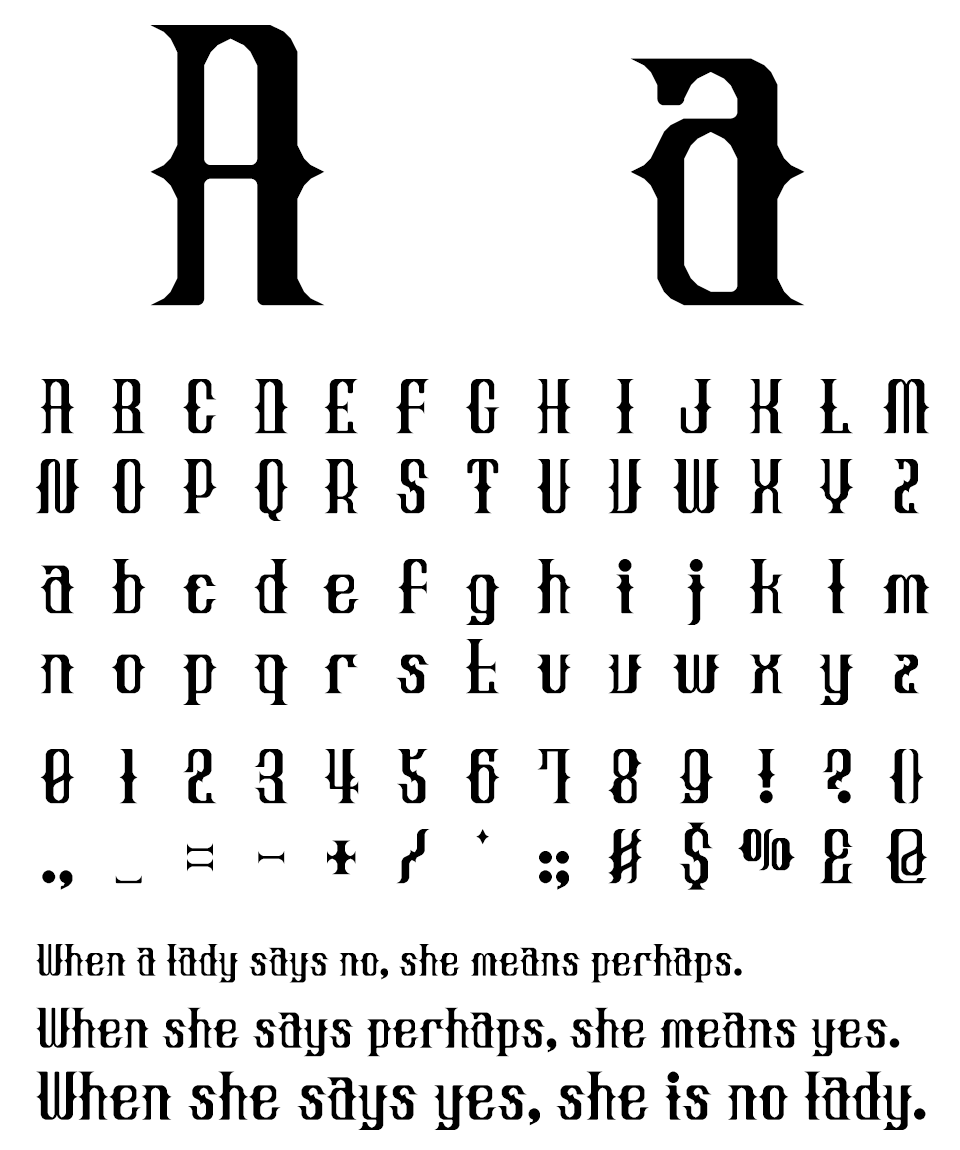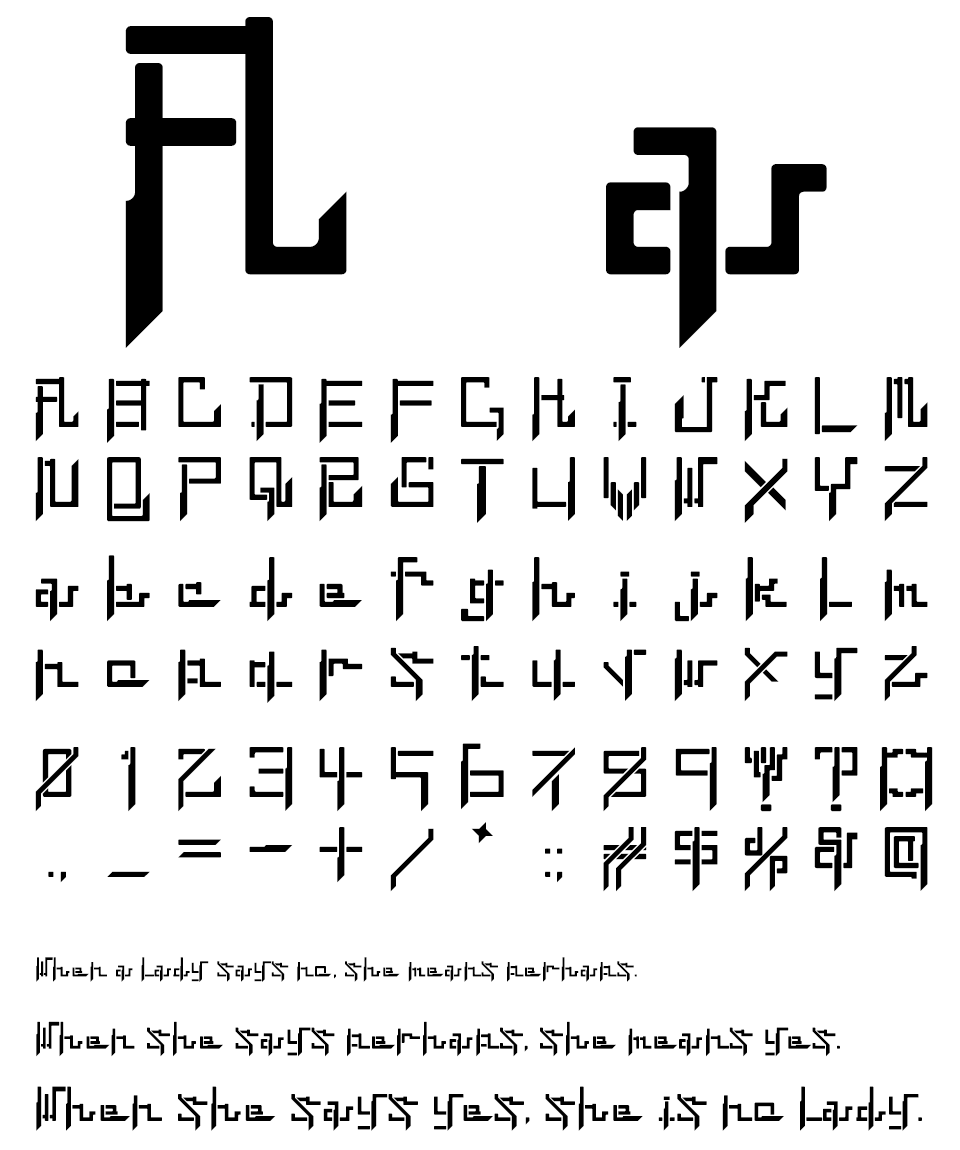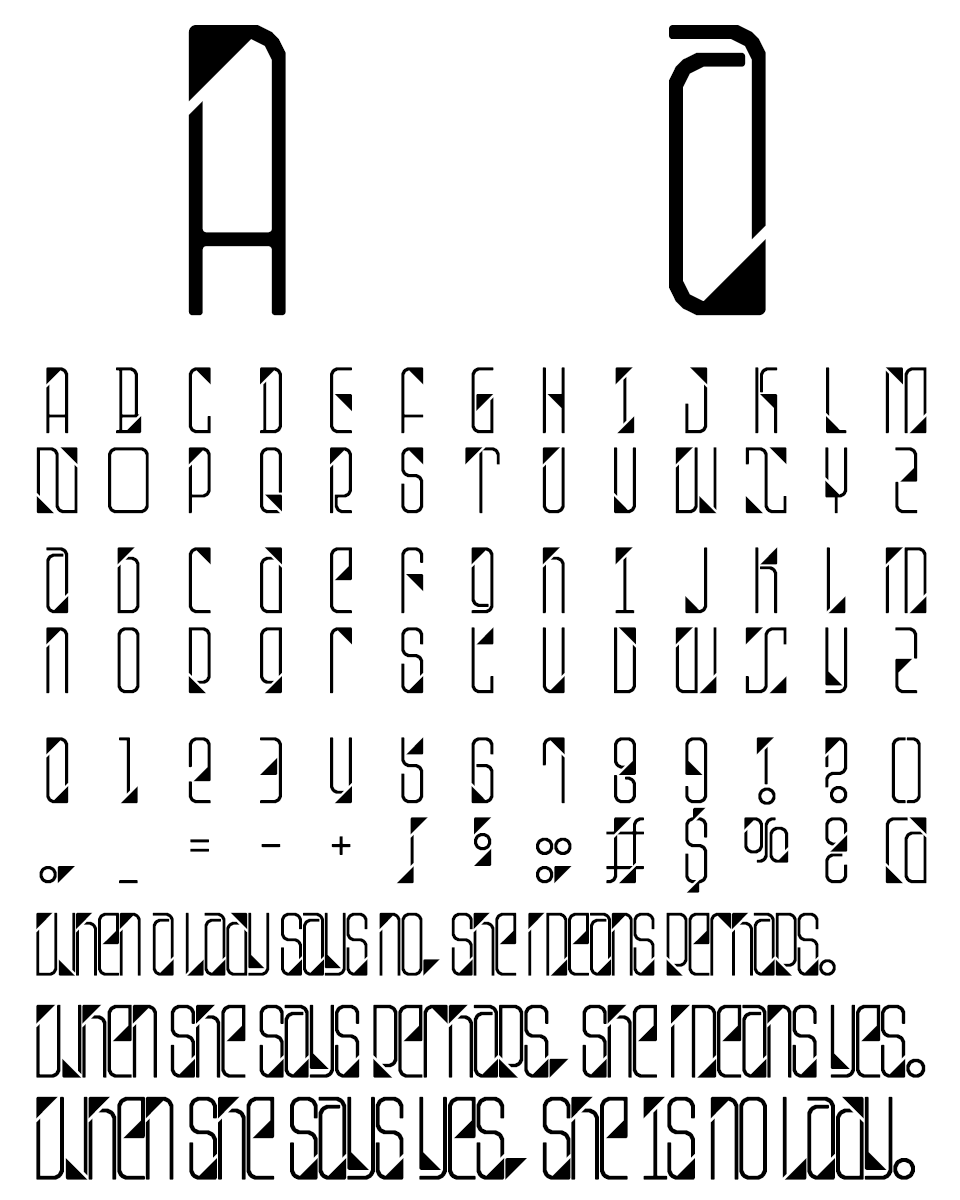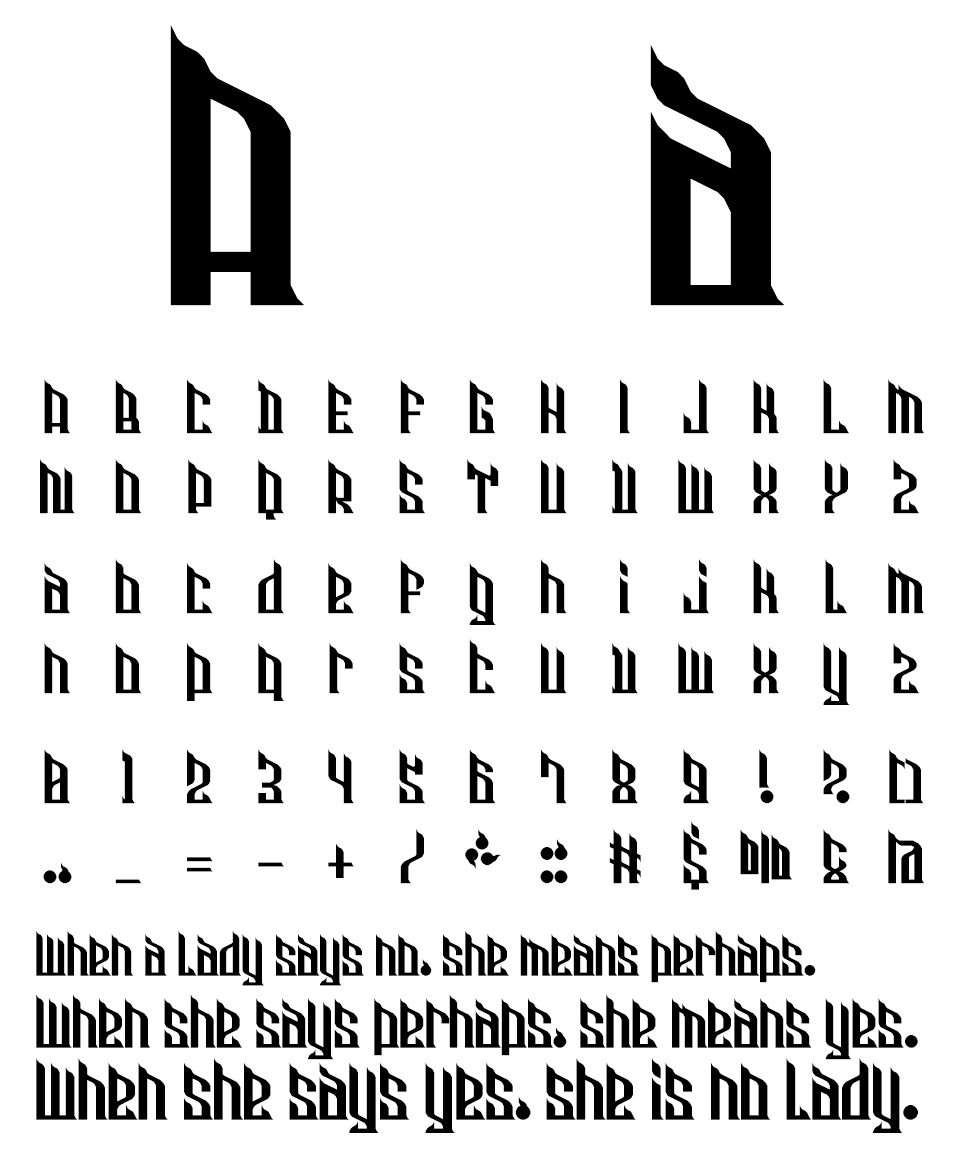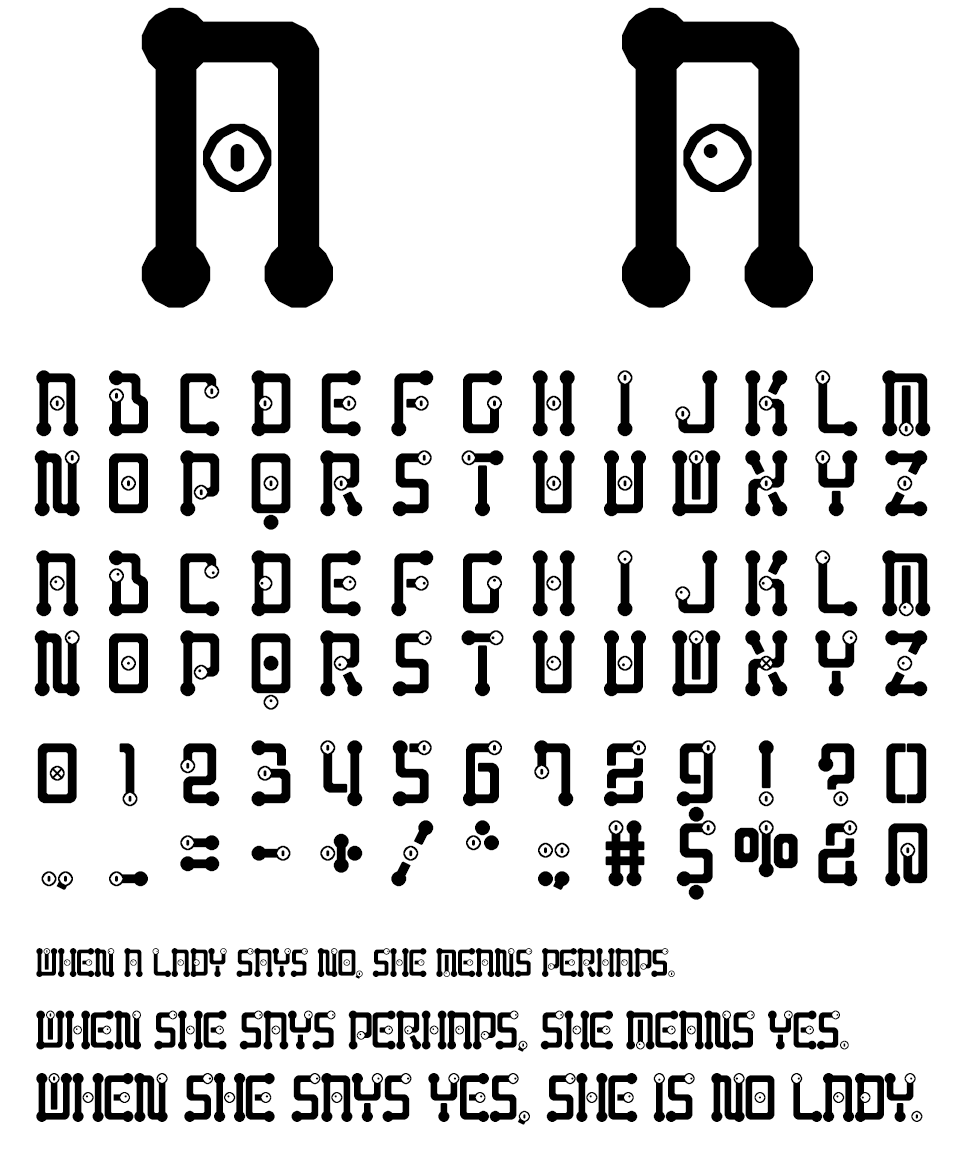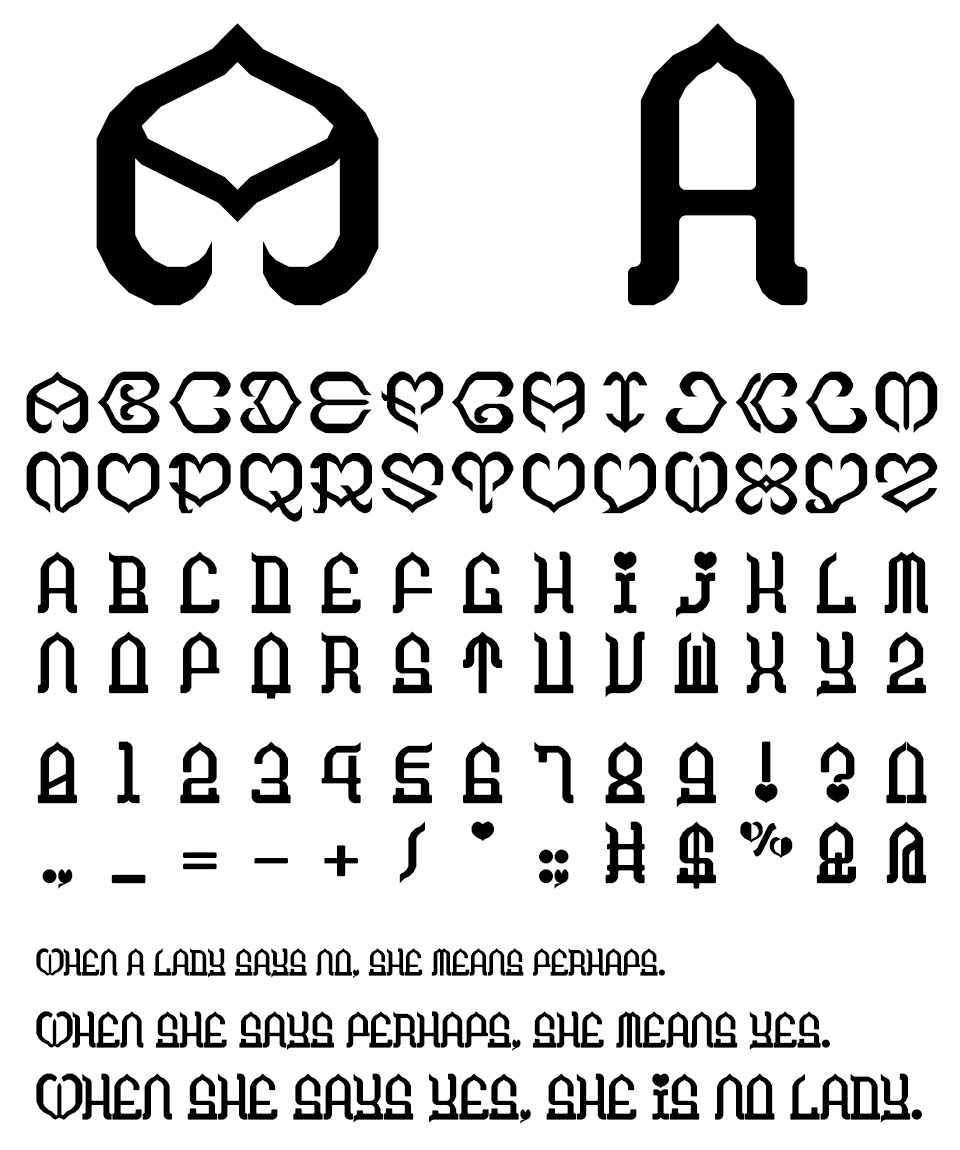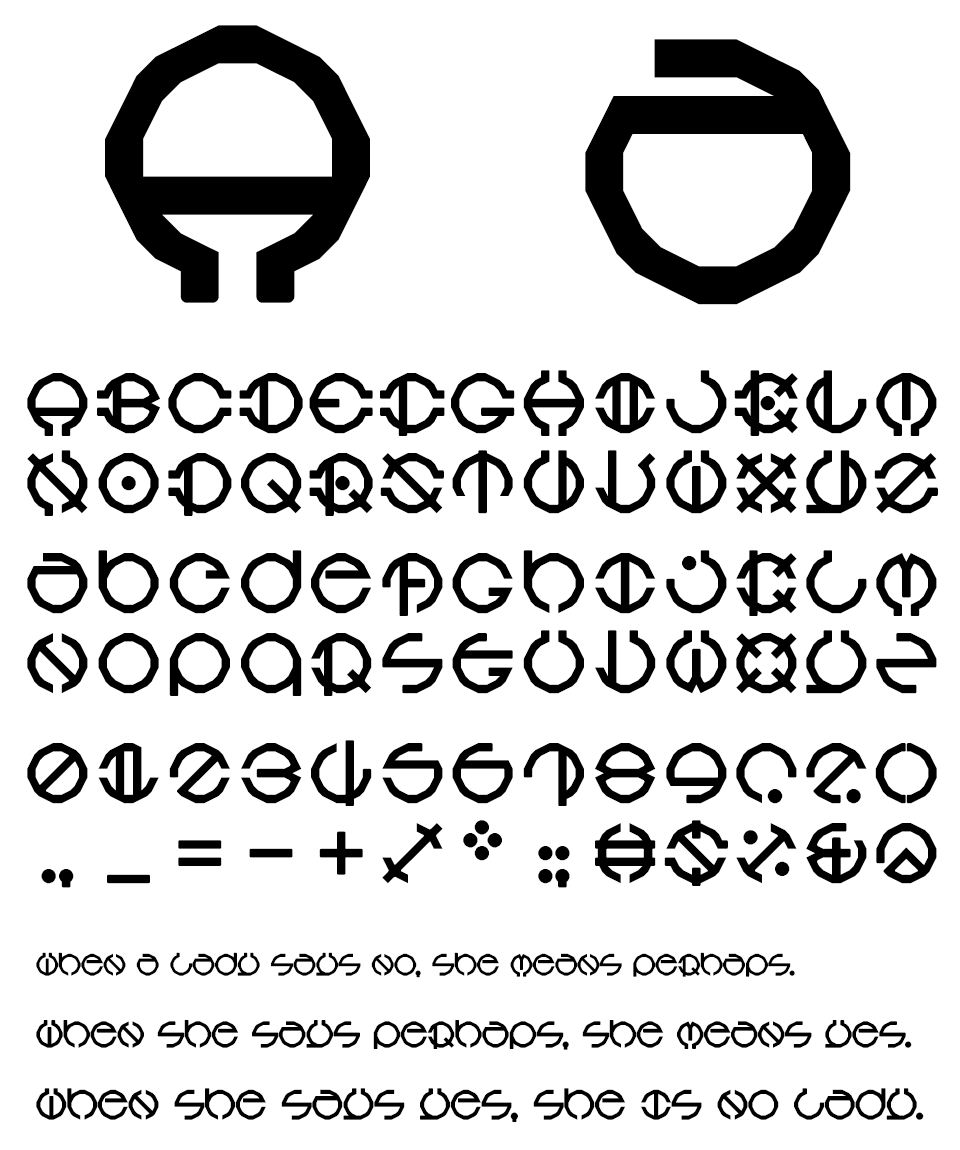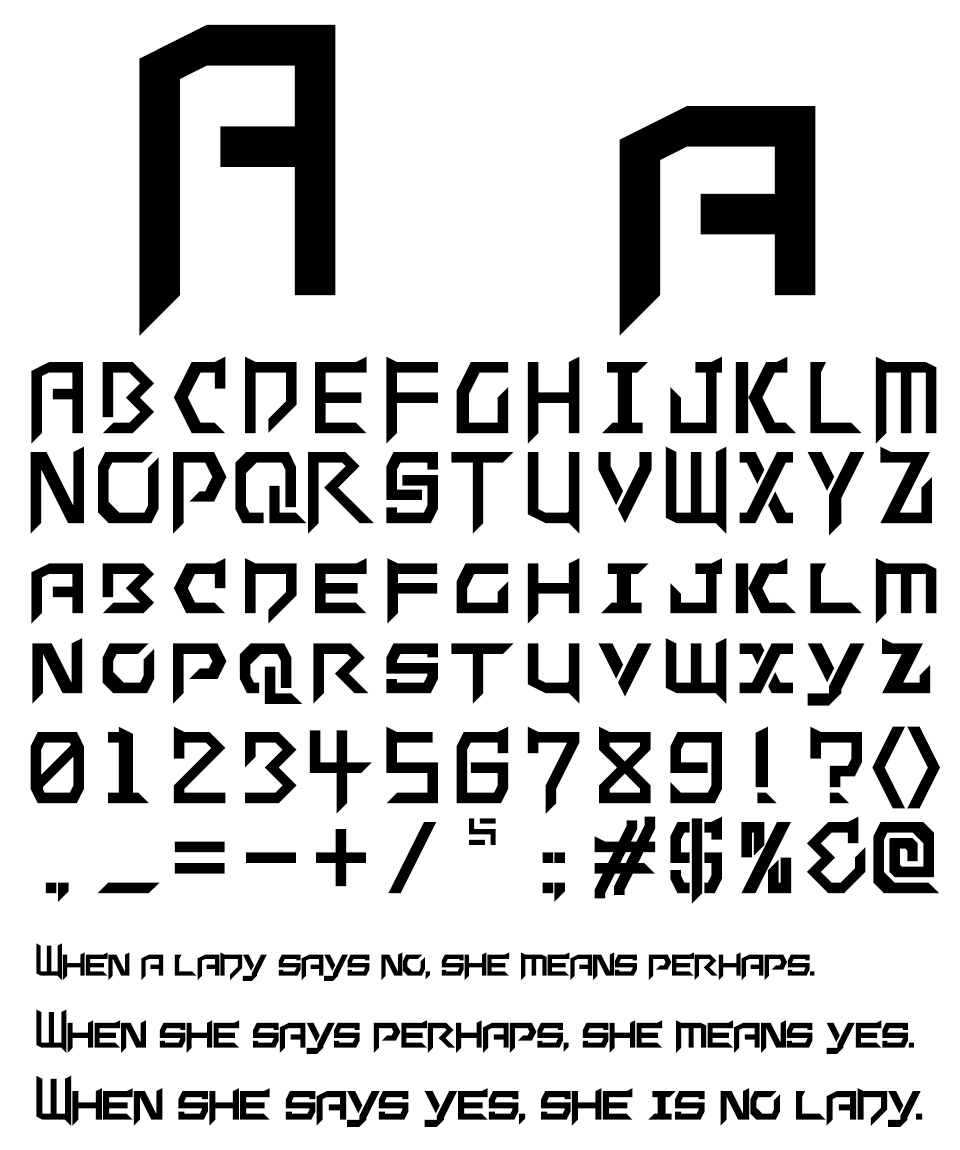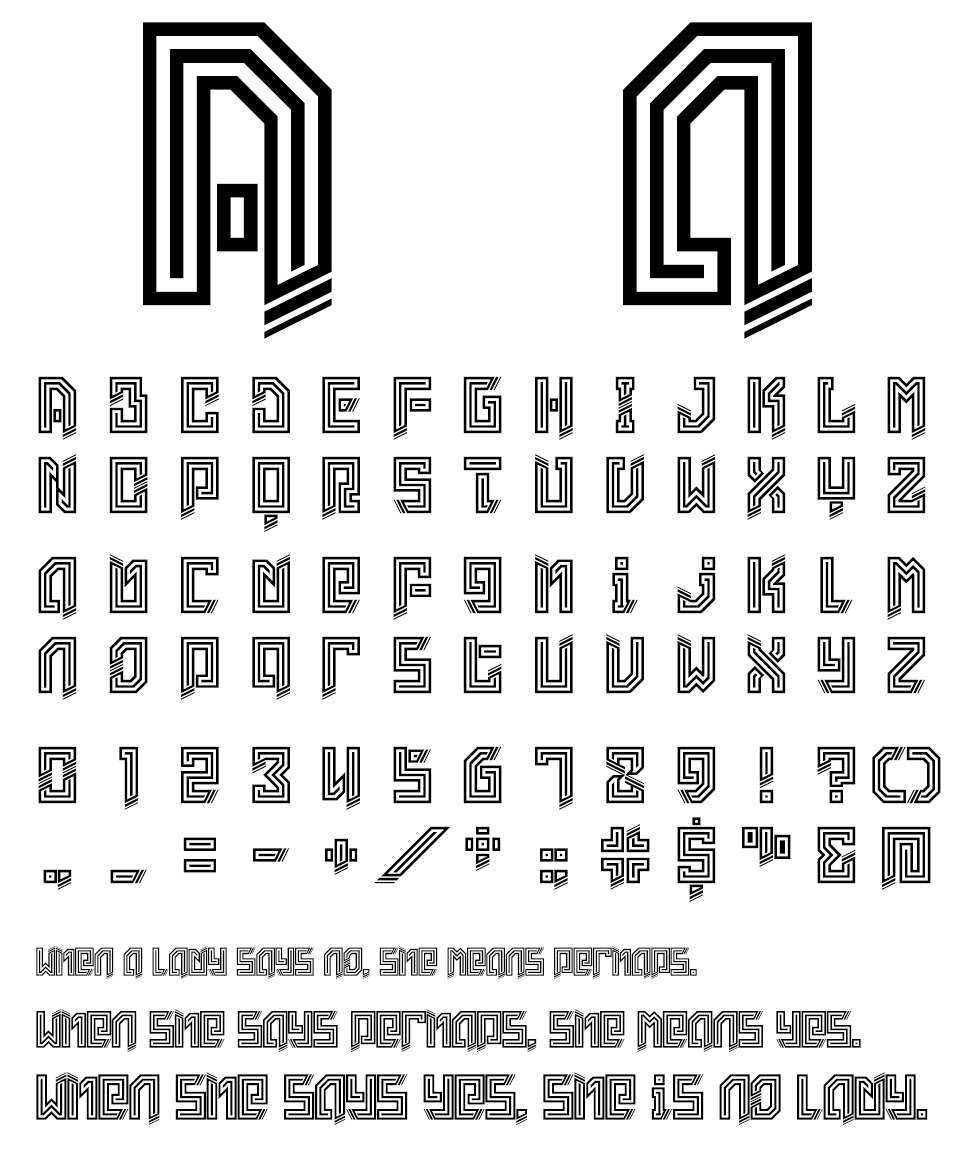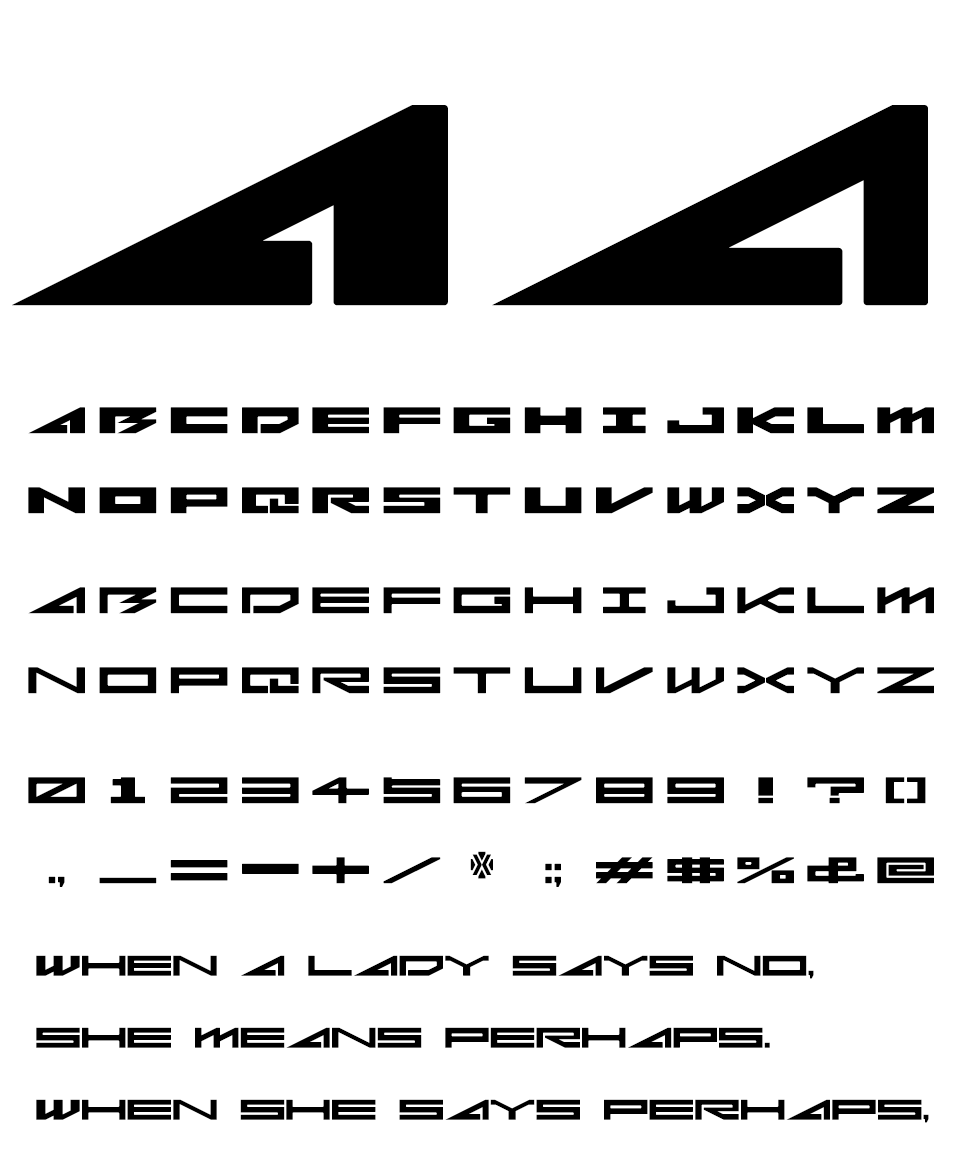
そらマート オリジナリティ溢れる欧文書体を創出するブランド
オリジナリティ溢れる欧文書体を創出するブランド「そらマート」
小説家としても活動するそらまめ氏によるブランド「そらマート/SORAMART」が提供する欧文フォントは、オリジナリティを持ちながらも文字組みするとパチッと決まる、安定感と統一感のあるデザインを目指して制作されています。
「そらマート」について
元々小説家としても活動しており、自分の書いた小説のタイトルも自分でデザインしてみたいという思いから独学でフォント作りを始める。
そのうちにフォント制作自体にも魅力を感じ、小説の連載とフォント作りを公開する活動を続けています。
オリジナリティを持ちながらも、文字を並べていくと工業生産品的にパチッと決まる…そんな、安定感と統一感のあるデザインを作ることが目標としています。
1. Banana Moon Fizz 【NEW】
2. Black Zebra 【NEW】
3. Bounding Balls 【NEW】
4. Dots Wizard 【NEW】
5. Fraktur Flare 【NEW】
6. Lime Candy 【NEW】
7. Omochi Pop 【NEW】
8. Pyramid Step Puzzle 【NEW】
9. Surpriser D 【NEW】
10. Virus Edge Emblem 【NEW】
11. Slashed Serif 【NEW】
12. Popper Doppel 【NEW】
13. Night Crow Beak
14. Slash KATANA
15. Tip Tap Top
16. Flare Wire
17. Insect Walk Eyes
18. Heart Queen
19. Orbit Core
20. Cyber Metal Core
21. Solid Ghost
22. Wired Wide Bold
23. Ink Dot Melt
24. Koro Koro Army
25. Graviton Pile Slashed
26. Fang and Claw
1. Banana Moon Fizz
,sora Banana Moon Fizz イメージ そらマート Banana Moon Fizz 文字見本
Banana Moon Fizz
そらマート Banana Moon Fizz 書体見本
”三日月”をイメージした縦長フォントに、”カクテル”をイメージしたドット・グラデーション加工を施しました。
2. Black Zebra
,sora Black Zebra イメージ そらマート Black Zebra 文字見本
Black Zebra
そらマート Black Zebra 書体見本
ひげ文字="ブラックレター"に、シマウマをモチーフにした縞模様を組み合わせたフォントです。
3. Bounding Balls
,sora Bounding Balls イメージ そらマート Bounding Balls 文字見本
Bounding Balls
そらマート Bounding Balls 書体見本
弧を描いて跳ねるボールをモチーフにした、縦長細字フォントです。
4. Dots Wizard
,sora Dots Wizard イメージ そらマート Dots Wizard 文字見本
Dots Wizard
そらマート Dots Wizard 書体見本
円形ドットを打ち込んで作った、装飾付き縦長フォントです。
5. Fraktur Flare
,sora Fraktur Flare イメージ そらマート Fraktur Flare 文字見本
Fraktur Flare
そらマート Fraktur Flare 書体見本
クラシカルな装飾付きのフォント、"ドイツ文字"こと"Fraktur"をモチーフにしたフォントです。
6. Lime Candy
,sora Lime Candy イメージ そらマート Lime Candy 文字見本
Lime Candy
そらマート Lime Candy 書体見本
キャンディをイメージして、”さわやかさ”の表現をめざしたシルエット風フォントです。
7. Omochi Pop
,sora Omochi Pop イメージ そらマート Omochi Pop 文字見本
Omochi Pop
そらマート Omochi Pop 書体見本
餅をモチーフに、可愛らしさの表現をめざした丸文字フォントです。
8. Pyramid Step Puzzle
,sora Pyramid Step Puzzle イメージ そらマート Pyramid Step Puzzle 文字見本
Pyramid Step Puzzle
そらマート Pyramid Step Puzzle 書体見本
”階段ピラミッド”をモチーフにしたドット調フォントに、タイルをイメージした装飾を加えました。
9. Surpriser D
,sora Surpriser D イメージ そらマート Surpriser D 文字見本
Surpriser D
そらマート Surpriser D 書体見本
ちょっとパンクな印象をめざした、四角いシルエットの太字フォントです。
10. Virus Edge Emblem
,sora Virus Edge Emblem イメージ そらマート Virus Edge Emblem 文字見本
Virus Edge Emblem
そらマート Virus Edge Emblem 書体見本
”ウイルス”をイメージして、刺々しいデザインをめざしたフォントに色抜き装飾を施しました。
11. Slashed Serif
,sora Slashed Serif イメージ そらマート Slashed Serif 文字見本
Slashed Serif
そらマート Slashed Serif 書体見本
斜線をモチーフにした、サイバーパンク調のブラックレター・フォントです。
12. Popper Doppel
,sora Popper Doppel イメージ そらマート Popper Doppel 文字見本
Popper Doppel
そらマート Popper Doppel 書体見本
枠線フォントを重ね合わせて、立体感を表現することをめざしたフォントです。
13. Night Crow Beak
,sora Night Crow Beak イメージ そらマート Night Crow Beak 文字見本
Night Crow Beak
そらマート Night Crow Beak 書体見本
鳥のクチバシをモチーフに、レトロでちょっと怪しい雰囲気を目指したフォントです。
14. Slash KATANA
そらマート Slash KATANA イメージ そらマート Slash KATANA 文字見本
Slash KATANA
そらマート Slash KATANA 書体見本
刀をモチーフにした、サイバーパンク調のフォントです。
15. Tip Tap Top
そらマート Tip Tap Top イメージ そらマート Tip Tap Top 文字見本
Tip Tap Top
そらマート Tip Tap Top 書体見本
三角形と曲線をモチーフに、軽やかなリズムの表現を目指したフォントです。
16. Flare Wire